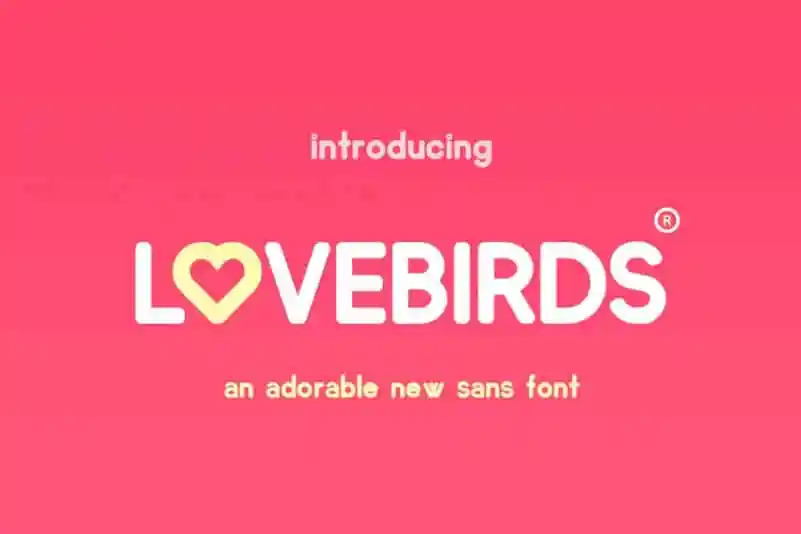
Lovebirds Sans Font
Adorei a oportunidade de introduzir Lovebirds Sans Font para vocês! Esta moderna tipografia sem serif oferece linhas aguçadas e formas levementes, criando um estilo único e elegante perfeito para qualquer projeto gráfico. Através do designer zziplex, este font vem da Salt & Pepper Designs e é uma opção divertida de usar em conjunto com outros tipos ou como fonte única por si só. Para os amantes de letras e, obviamente, aqueles que não são tão apaixonados mas ainda apreciam um belo tipo, Lovebirds Sans Font é perfeito. Se você gosta de adicionar estilo a seus projetos, este font oferece uma maneira de fazer isso de forma fácil e versátil, se combinando bem com outros designs ou se mantendo forte o bastante para ser usada sozinha. Para aqueles entre nós que ainda não são apaixonados pelo Lovebirds Sans Font, mas já amam as letras e querem adicionar algo novo a suas criações, este font é uma ótima escolha. Ele oferece um estilo único capaz de destacar seu trabalho sem ser invasivo ou carregado. Engata-se à sua lista de opções para criar um design perfeito com a Lovebirds Sans Font do zziplex!